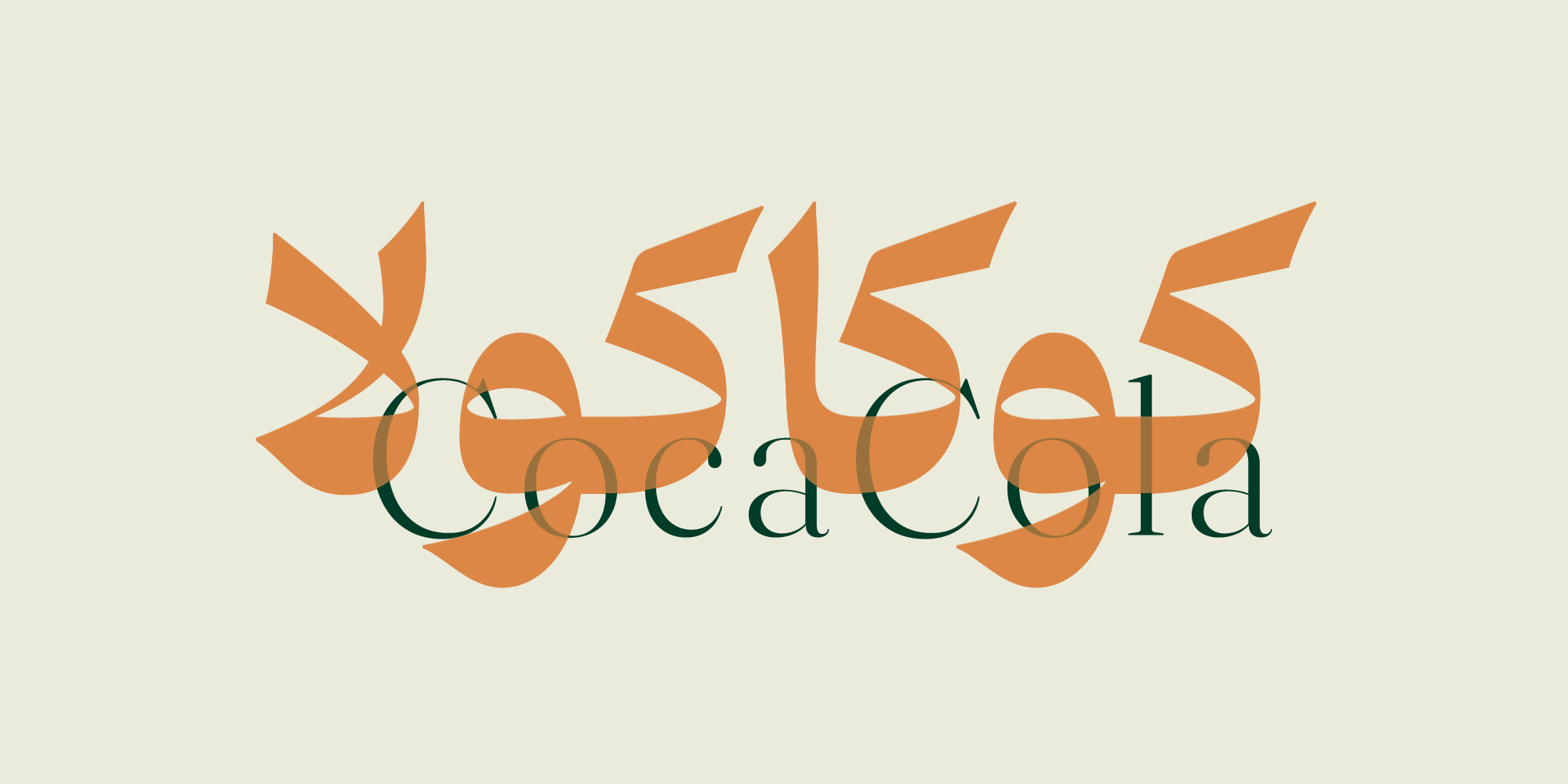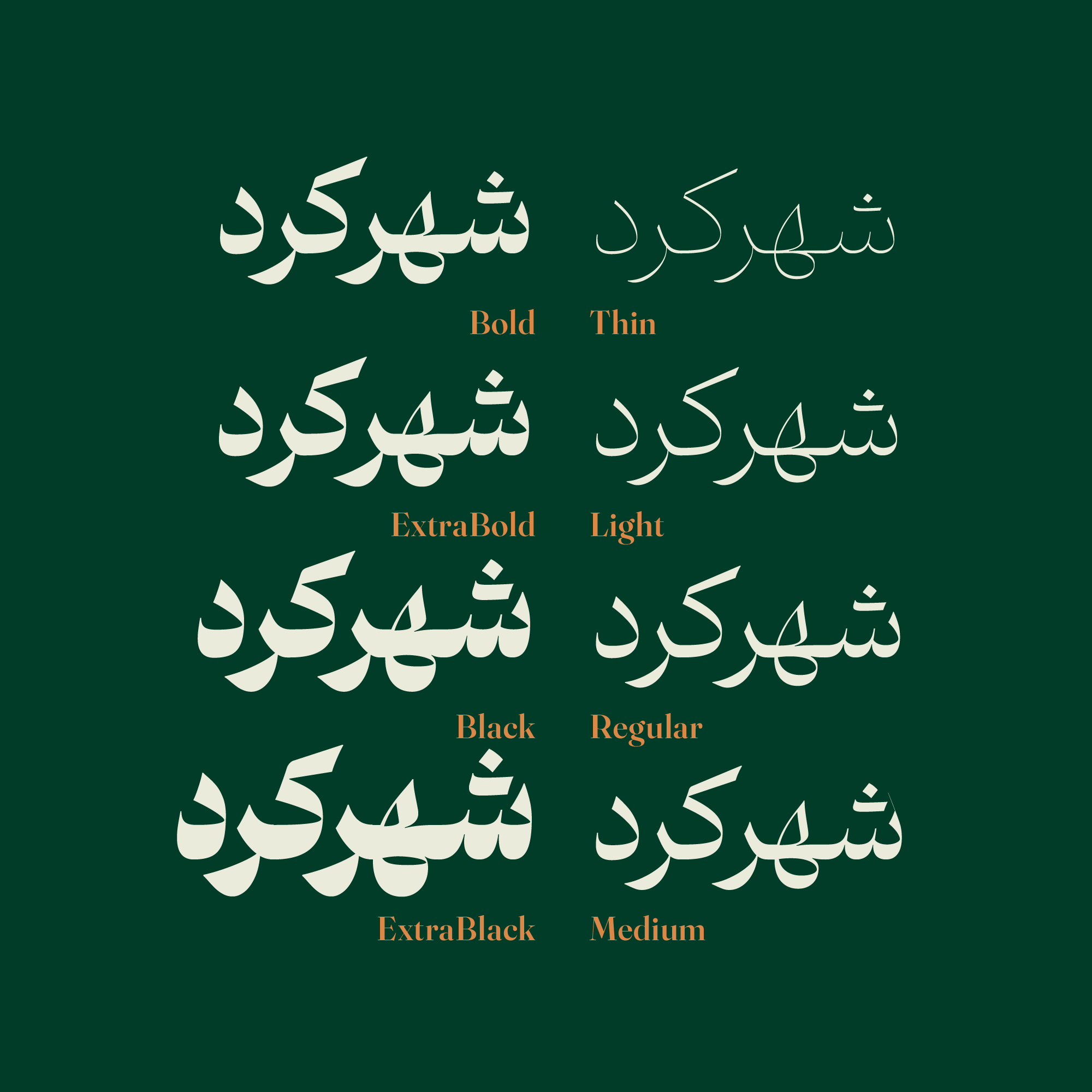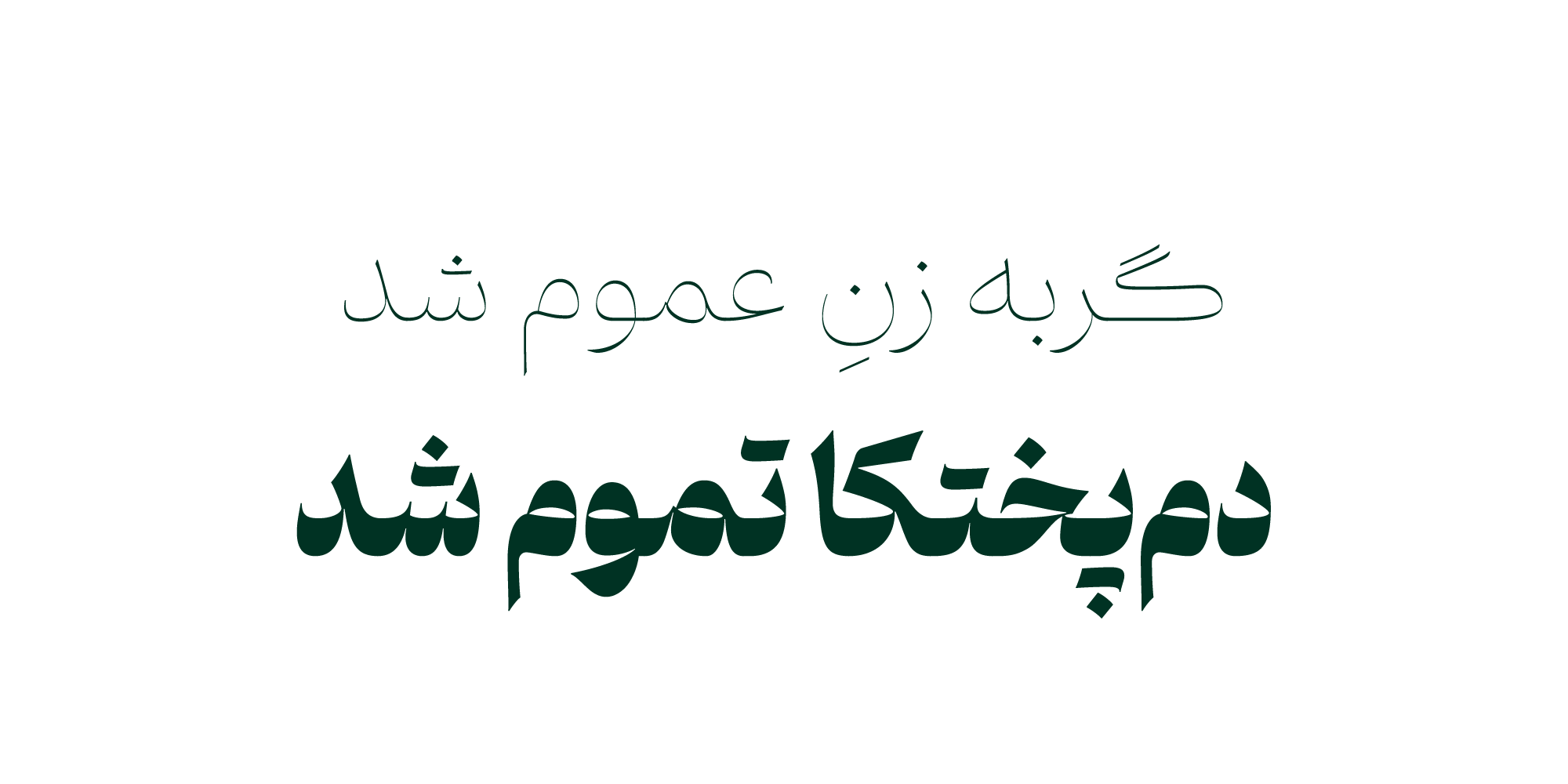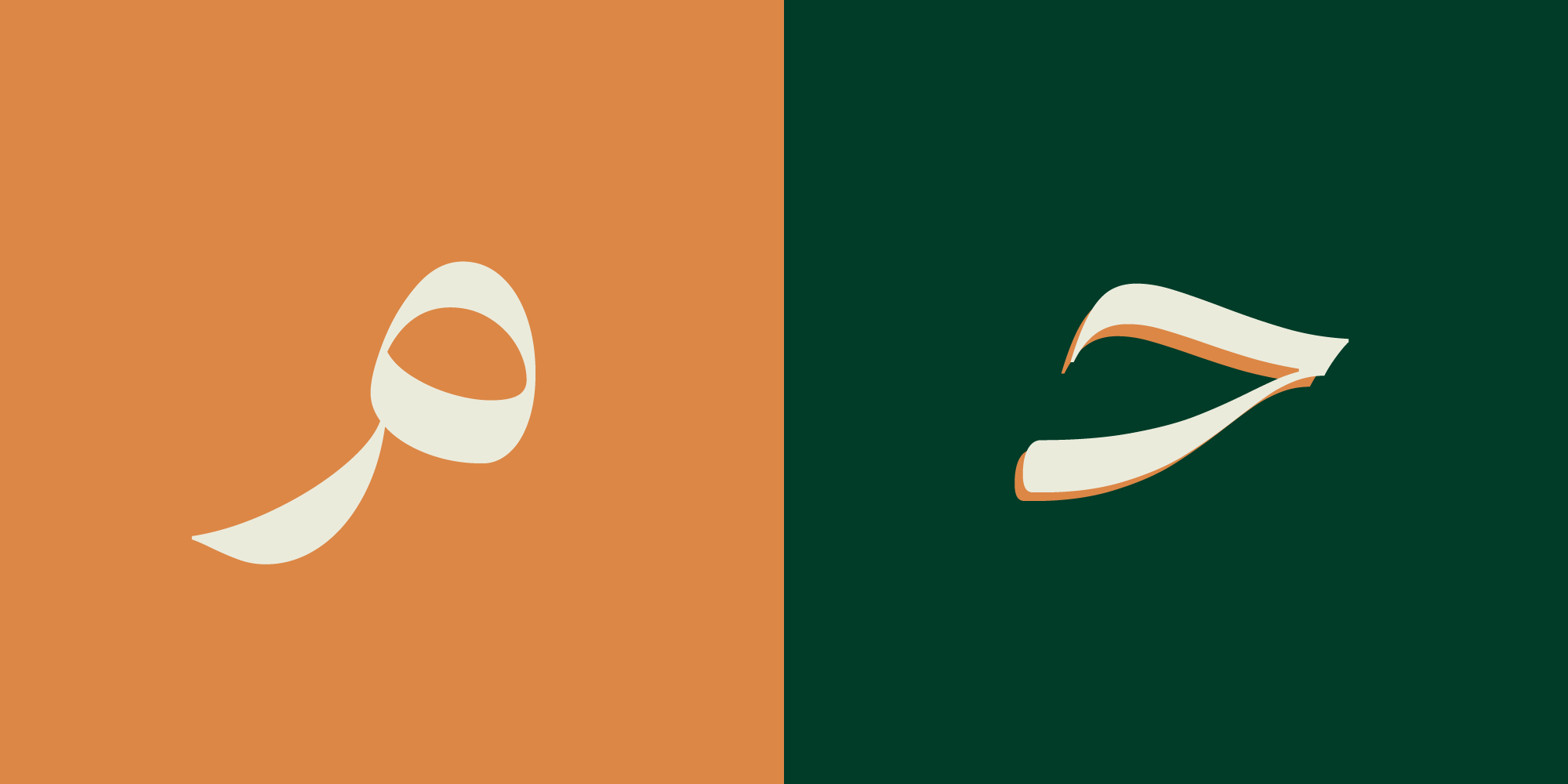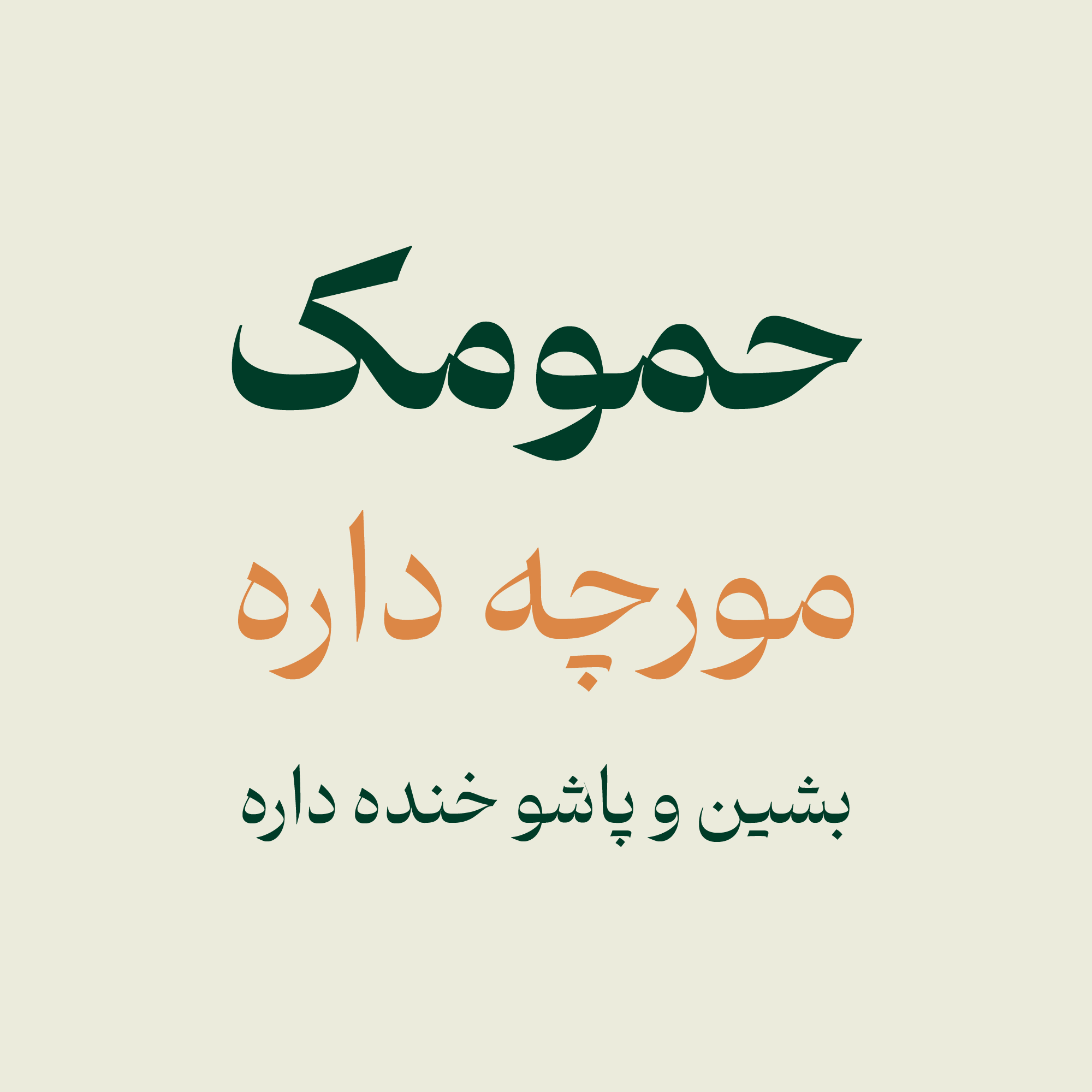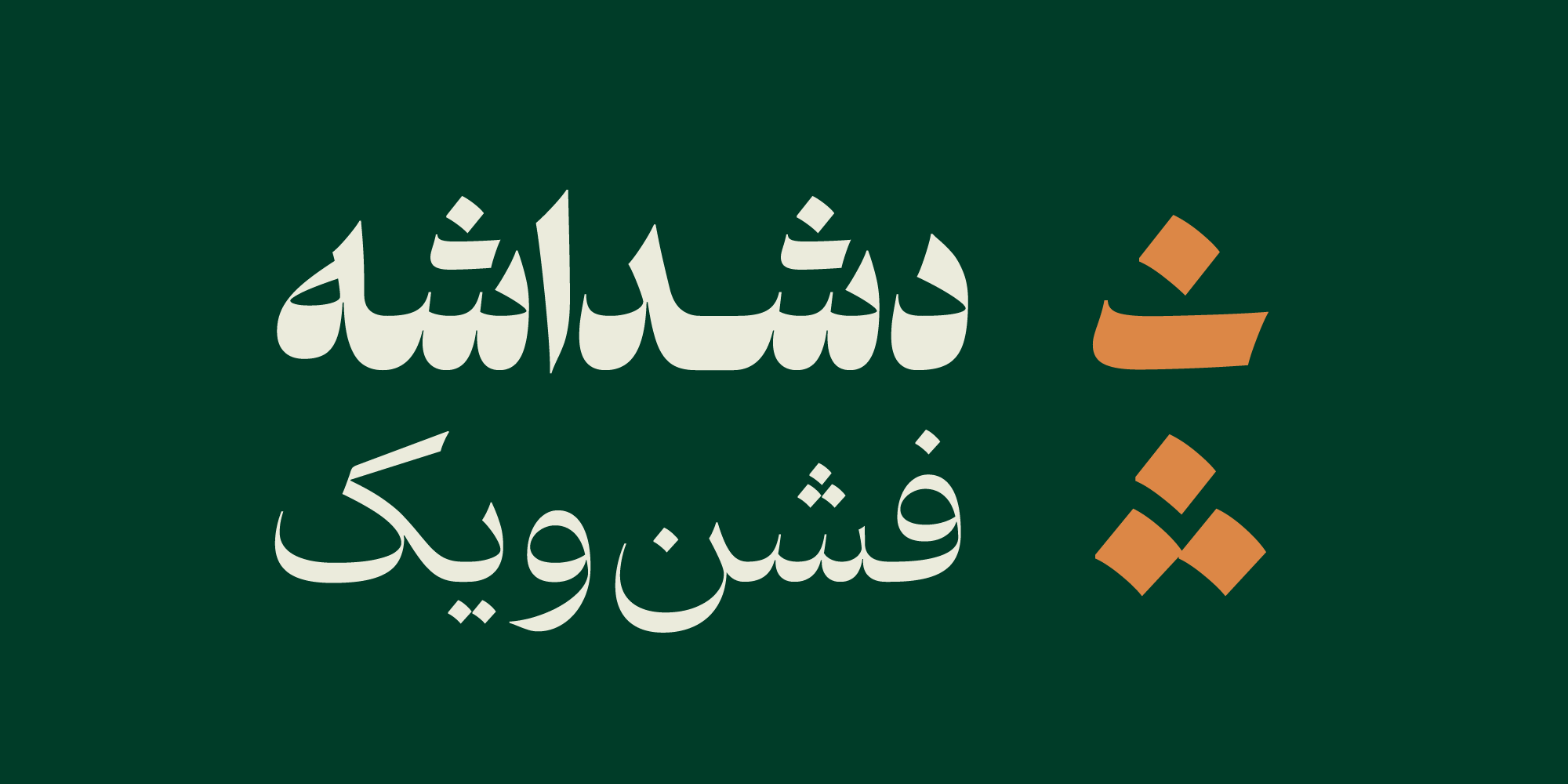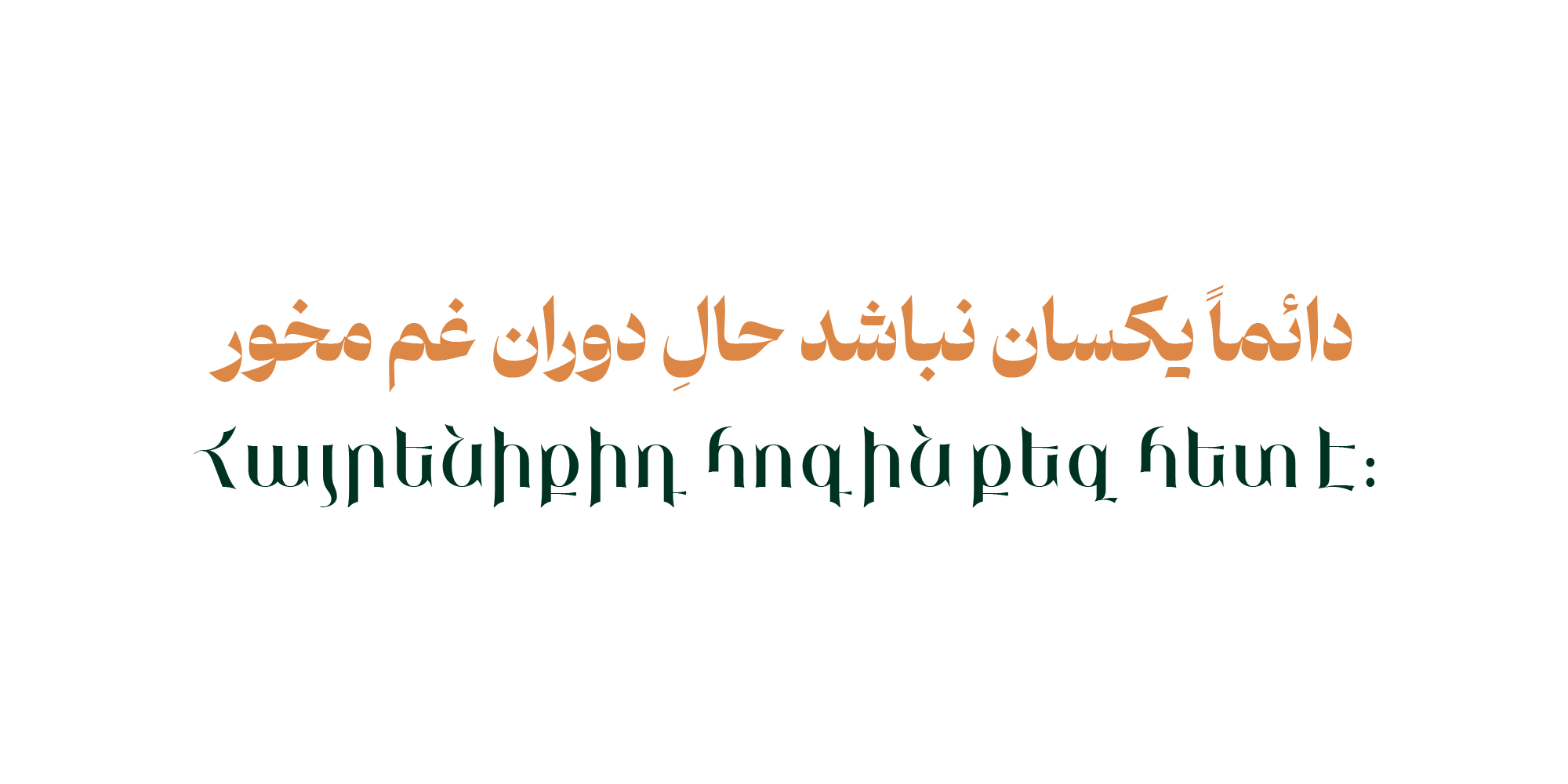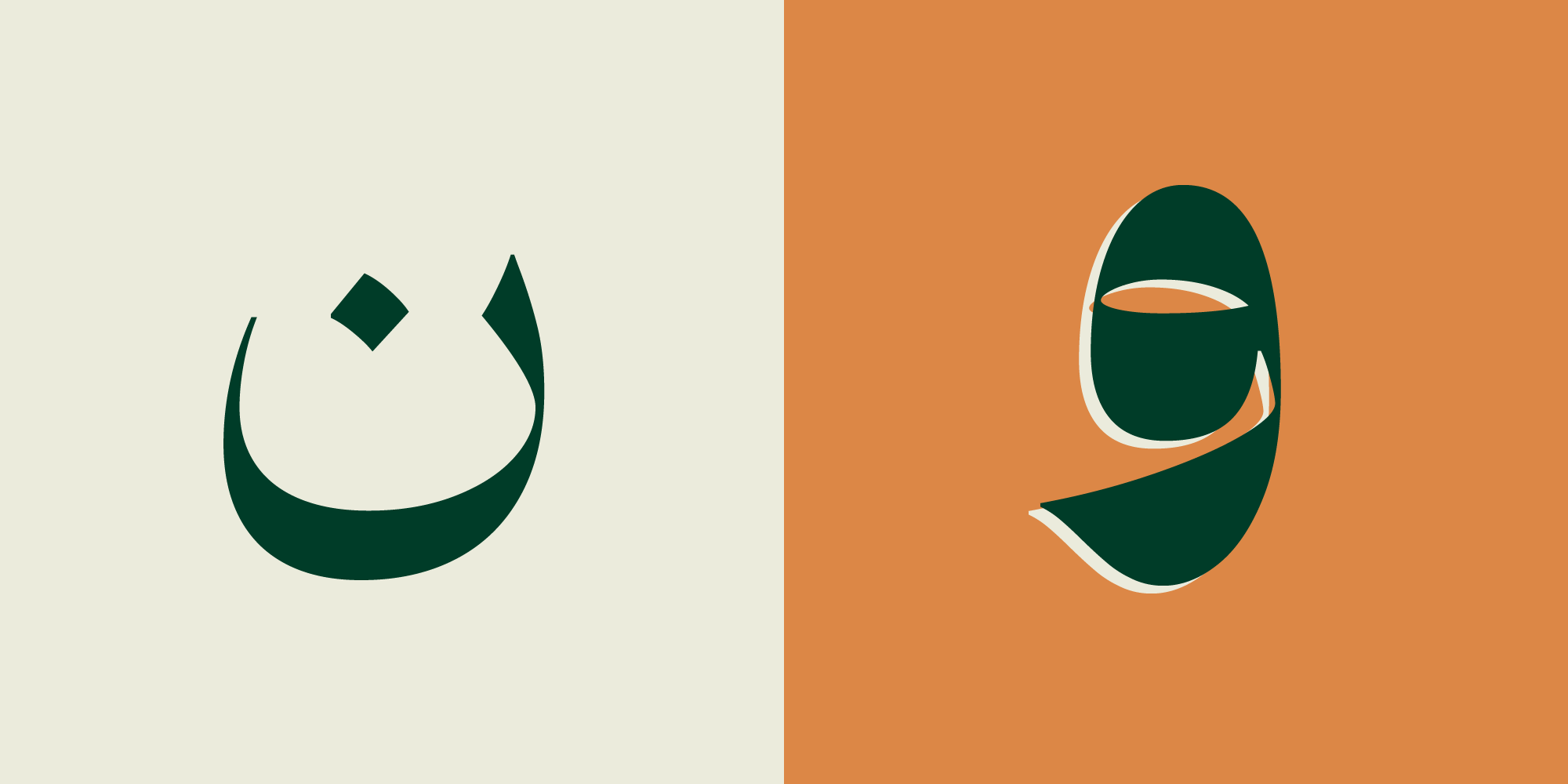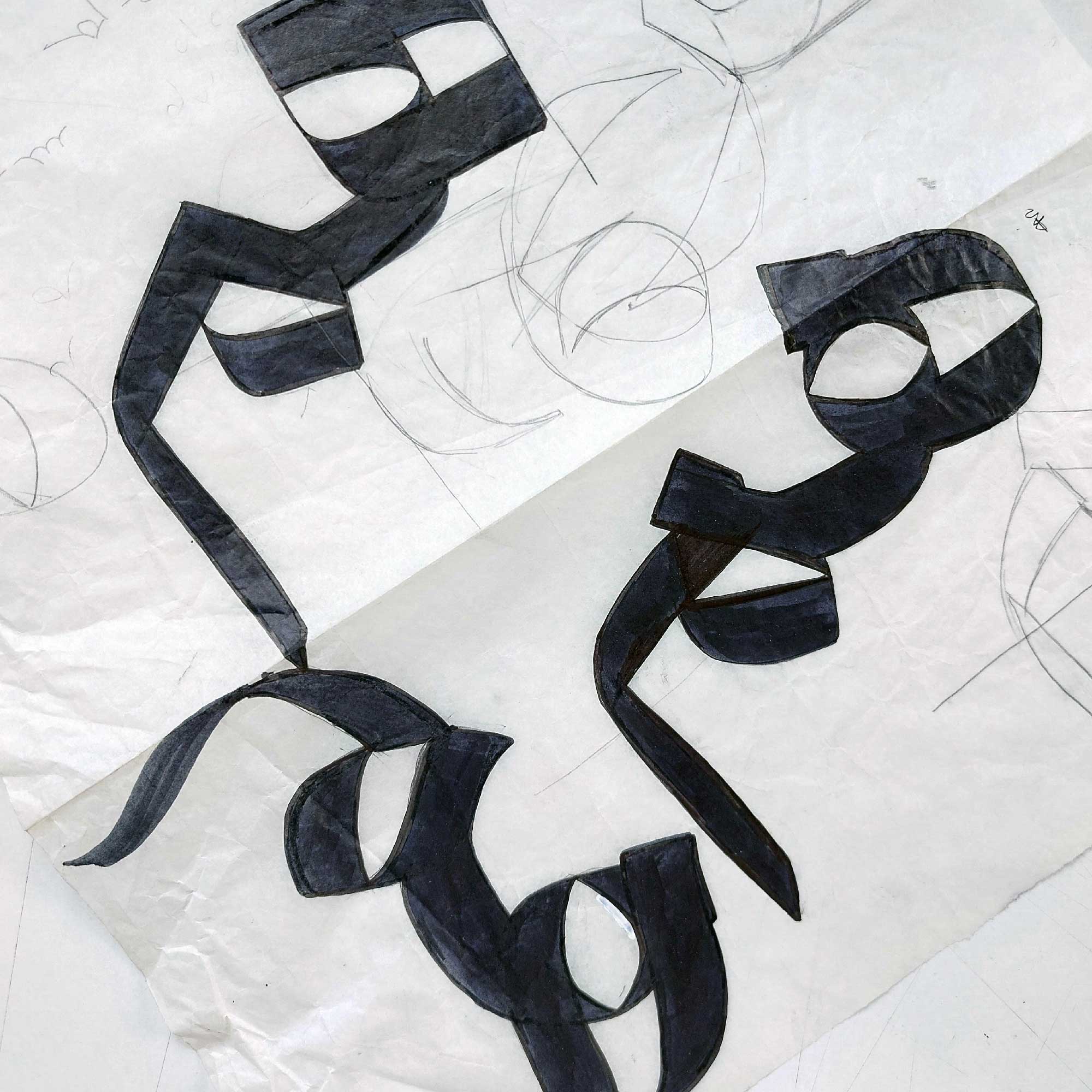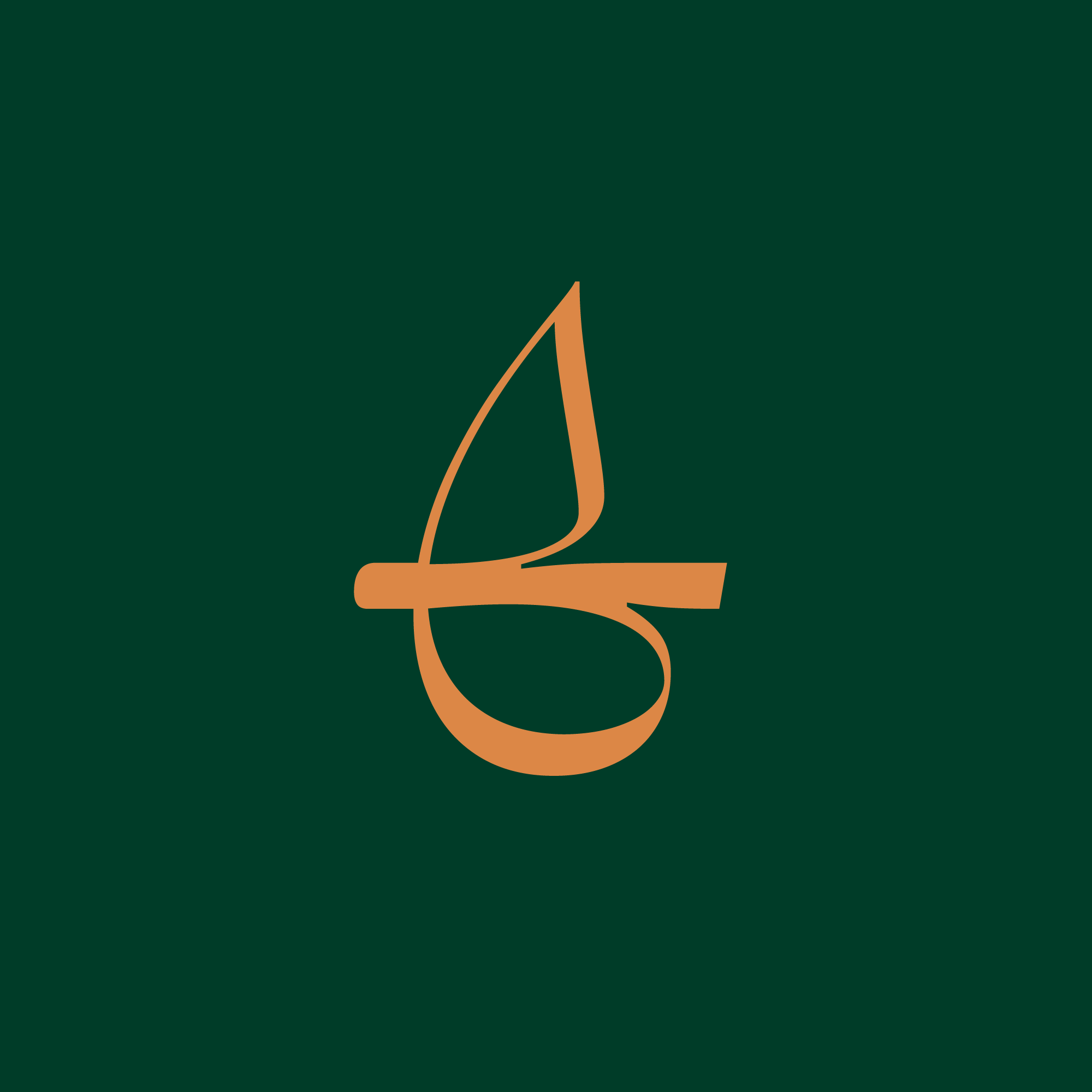
تنوع وزنها در فونت دوران
فونت دوران دارای ۸ وزن (Thin, Light, Regular, Medium, Bold, ExtraBold, Black, ExtraBlack) و نسخهی وریبل است.
امکان تغییر شکل نقطهها
دو نوع نقطه در فونت وجود دارد، چسبیده و جدا.
ارمنی
کاراکترهای زبان ارمنی بهصورت اختصاصی برای فونت دوران طراحی شدهاند.
ریال و تومان
با فعال کردن Stylistic Sets 2 میتوانید نمادهای اختصاصی ریال و تومان را فعال کنید و نمادهای ریال عربستان و درهم امارات با Stylistic Sets 3 در دسترساند.
تراز عمودی اعداد
با فعال کردن Stylistic Sets 4 میتوانید تراز عمودی اعداد، علائم مرتبط و نمادهای پولی را تنظیم کنید.
اعداد همعرض
اعداد همعرض برای زیرهمنویسی اعداد و نوشتن در جدولهاست.
چندزبانه
دوران از زبانهای فارسی، انگلیسی، عربی، ارمنی، اردو، کردی و جاوی پشتیبانی میکند
ترکیبها و حروف جایگزین
فونت دوران دارای ترکیبات (Ligature) و حروف جایگزینی (Alternative) است که تاثیر بسیاری روی زیبایی نوشته میگذارد.
زبان بصری و الگوی دیزاین فونت
فونت دوران در کاربرد